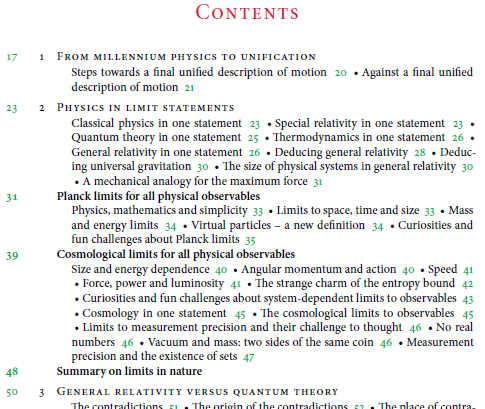
Gibt es einen Namen für diese Art von Inhaltsverz.?
gibt es einen Stil, der diese Art von Inhaltsverzeichnis "erfunden" hat, also hat dieses Inhaltsverzeichnis einen bestimmten Namen gegeben bekommen?
I Einleitung
I.1 Eine Überschrift 2 I.2 Noch eine Überschrift 5 I.3 ...
II Mehr Zeug
II.1 Überschrift der ersten Sektion 12 II.2 Üb...
Ich hoffe, die Idee wird klar? :) Also die Kapitelüberschriften wären natürlich alle größer und oder als Kapitälchen gesetzt und z.B. könnte zwischen Seitenzahl und Sektionsziffer noch mehr Abstand.
Ich habe mich gerade nur spontan daran erinnert, dass ich das schon einmal irgendwo so gesehen habe.
(Für ein Dokument von mir würde ich das gerne in LaTeX nachbasteln, nur finde ich da nichts brauchbares.)
Mir erschließt sich der Sinn einer gemischten Verwendung (römisch/arabisch) nicht. Ich finde das eher verwirrend und dem Sinn einer Gliederung widersprechend. Wo wird denn eine derartige Gliederung verwendet?
Ich wollte sie mal ausprobieren. Wo genau derartige Gliederung schon verwendet wurde, weiß ich gerade nicht, aber ich habe sie definitiv schon einmal vor mir gehabt.
Die römischen Ziffern waren jetzt nur beispielhaft eingebaut. :)
… Die römischen Ziffern waren jetzt nur beispielhaft eingebaut. :)
Beispielhaft für was? Ich versteh’s grad nicht, willst du nun gemischte Zahlen verwenden oder was genau ist deine Frage?
Ich will keine gemischte Gliederung. Beispielhaft war wohl der falsche Ausdruck, die Formatierung sollte nur schnell klar werden.
Ich habe jetzt doch die Quelle der Idee wiedergefunden: Die Bände der Reihe "Motion Mountain - The Adventure of Physics", zu finden auf http://www.motionmountain.net/.
Ich will keine gemischte Gliederung. Beispielhaft war wohl der falsche Ausdruck, die Formatierung sollte nur schnell klar werden. …
Da steig ich jetzt komplett aus. Was denn nun? Eine Formatierung, die du gar nicht willst, aber zeigst, sollte schnell klar werden. Klar ist grad gar nix. Oder geht das nur mir so?
Ich werde nur arabische Ziffern benutzen. Also würde ich gerne wissen wollen, ob diese Art von Inhaltsverzeichnis
1 Einleitung
1.1 Eine Überschrift 2 1.2 Noch eine Überschrift 5 1.3 ...
2 Mehr Zeug
2.1 Überschrift der ersten Sektion 12 2.2 Üb...
schon einen Namen hat bzw. sich etwas verbreitet hat. Falls ja, könnte ich mal nach den entsprechenden Stichwörtern nutzen und gucken was dazu schon existiert.
Ich würde halt selber mich nicht sooo gerne in das relevante LaTeX-Paket namens tocloft einarbeiten. Ich würde es aber im Falle des Falles machen, falls nicht schon irgendwo im Netz eine Grundlage als Einstiegshilfe dienen könnte. :)
Meinst Du so:
1
1.1
1.2
1.3
.
2
2.1
2.1.1
2.2
.
... und bist nur zu faul, das auch so zu tippen, oder hat es mit den seltsamen Zahlen ohne Punkt dahinter ...
1 Einleitung
1.1 Eine Überschrift 2 1.2 Noch eine Überschrift 5 1.3 ...
2 Mehr Zeug
2.1 Überschrift der ersten Sektion 12 2.2 Üb...
... und der Schreibung auf einer Zeile tatsächlich eine Bewandnis, die keiner hier rafft ...?
Es geht anscheinend um Inhaltsverzeichnisse nach diesem Muster:
nichtlineares-inhaltsverzeichnis-screenshot.png
• Grüne Zahlen: Seitenzahlen
• Schwarz Zahlen: Kapitelnummern
Außerdem enthält der Beispieltext noch unnummerierte Abschnitte und Unterabschnitte. (Der OP will diese in seinem Dokument wohl nummerieren.)
Ich vermute mal, dass die Frage sein sollte, was von dieser Art von Inhaltsverzeichnissen – in denen mehrere Unterabschnitte pro Zeile aufgeführt sind – zu halten ist.
Davon halte ich viel -- bei kleinem Format. Suhrkamp macht sowas beispielsweise sehr gut.
Gibt es überhaupt Inhaltsverzeichnisse, die einen speziellen Namen haben?
ich hab mal im großen, gelben LaTeX-Begleiter geblättert und bin auf titletoc gestoßen, das scheint zu können, was du willst..
Im Begleiter ab Seite 67ff. beschrieben.
ich hab mal im großen, gelben LaTeX-Begleiter geblättert und bin auf titletoc gestoßen, das scheint zu können, was du willst..
Im Begleiter ab Seite 67ff. beschrieben.
Mensch, jo, der war ja schon total eingestaubt. An den hatte ich gar nicht mehr gedacht ... :) :oops: Danke für den Tipp! :huhu: Hat das hier doch noch zu was geführt. :P
Falls jemand Interesse an einer Anfangslösung hat:
\usepackage{titletoc}
\contentsmargin{0pt}
\titlecontents{chapter}[1.5pc]
{\addvspace{2pc}\large}
{\rmfamily\scshape\thecontentslabel~}
{}
{~-~\thecontentspage}
[\vspace{2pt}]
\titlecontents*{section}[0pt]
{\small}
{\thecontentslabel~}
{}
{~-~\thecontentspage}
Also ob das Paket einen eigenen Befehl definiert ... kann gut sein. Zumindest gibt es Befehle für "Teil"-Verzeichnisse, also wenn das IVZ des Kapitels 3 unter dessen Überschrift detailliert ausgegeben werden soll. Aber wie genau die funktionieren, habe ich nicht angeguckt.
Der \tableofcontents hat bei mir auch das gewünschte Ergebnis ausgegegeben, daher würde ich den auch so weiter nutzen.